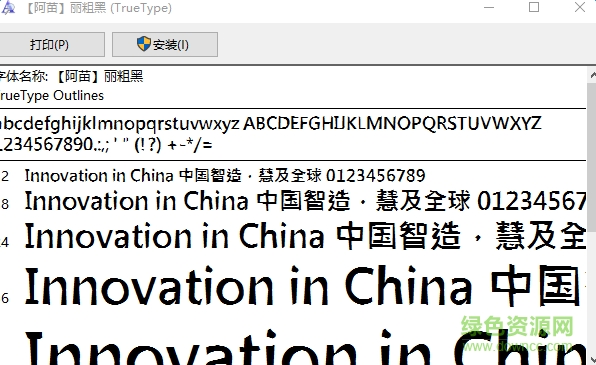
阿苗麗粗黑
阿苗麗粗黑字體是一款很不錯(cuò)的電腦黑體字體,這款字體最大的特色就是比一般字體要粗黑許多,但是這也是它的一個(gè)特色,所以并不影響它的使用,歡迎有需要的朋友來綠色資源網(wǎng)下載。
阿苗麗粗黑字體
阿苗麗粗黑字體是一款很好用的電腦字體,寫出來的字很好看,小編已經(jīng)幫大家試用過了,效果非常不錯(cuò)哦,大家可以放心使用。